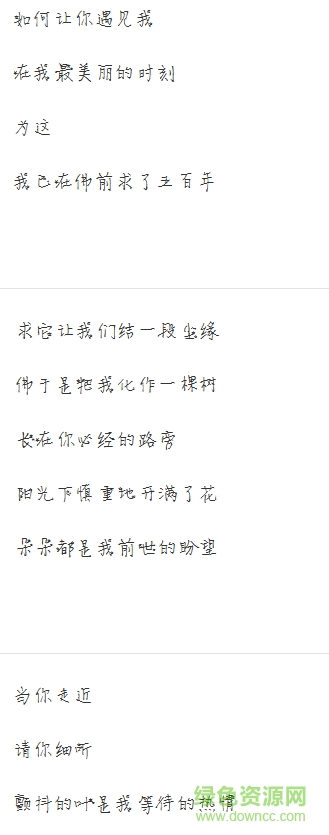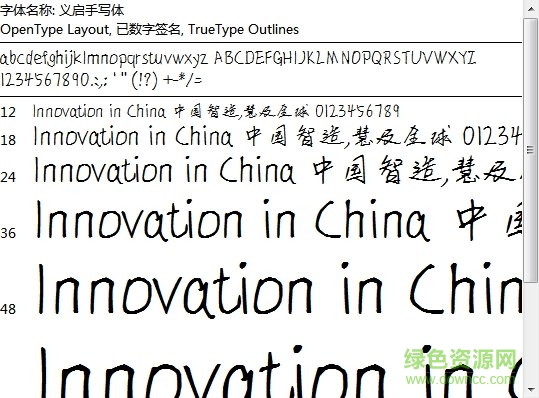
義啟手寫體ttf是義啟字庫官方推出一款好看的鋼筆四蹄,頗有瘦金體風(fēng)格,字體美觀大觀,非常適合情書表白、詩歌寫作等,需要的朋友請(qǐng)來綠色資源網(wǎng)下載吧!
義啟字庫以女孩筆跡為基礎(chǔ),融入天然、爽朗、以拙為巧等元素,設(shè)計(jì)出這款“義啟手寫體”。用筆灑脫自然,映帶婉轉(zhuǎn)但又不刻意雕飾。結(jié)構(gòu)處理是以拙為巧的哲學(xué)理念,收處緊密穩(wěn)如靜子,放處疏簡動(dòng)如脫兔。章法是手寫的靈魂,字與字筆斷意連卻自然天成。無故意為之但法度一體